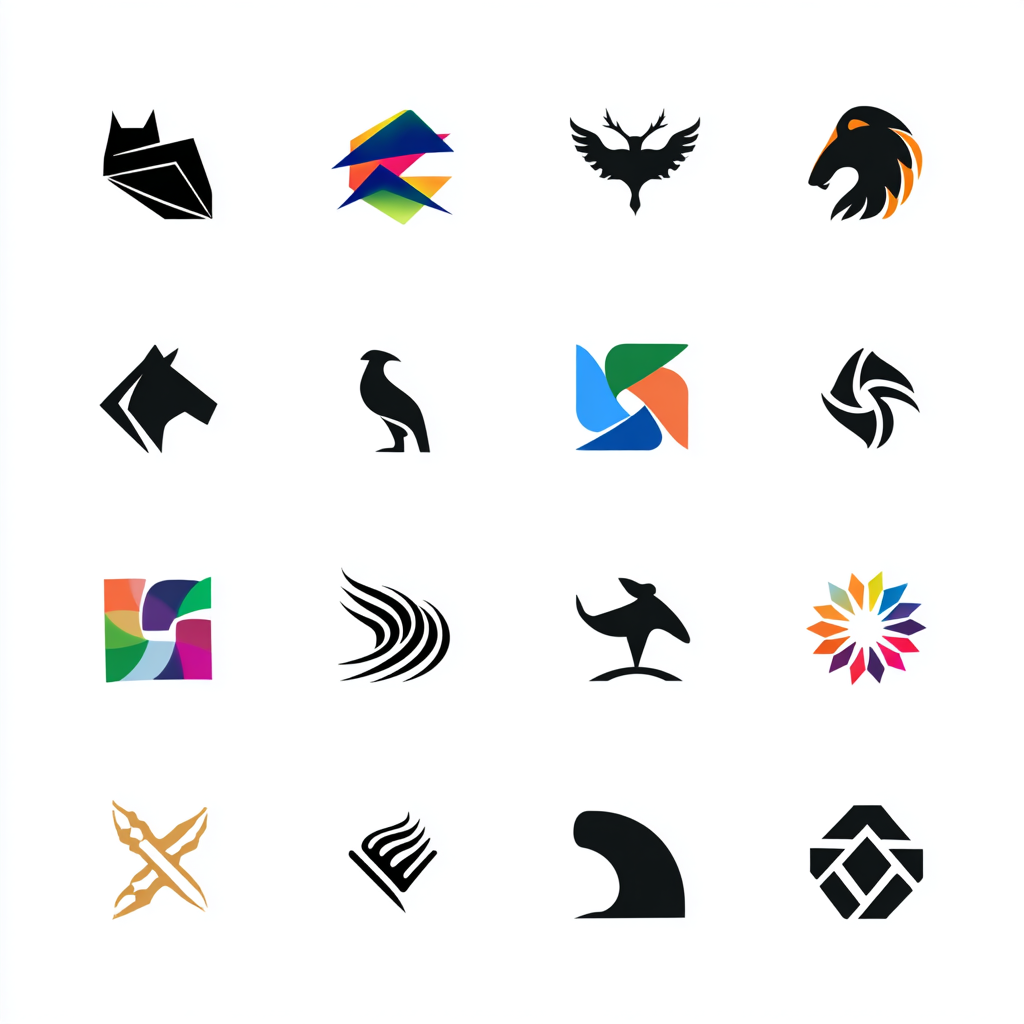
로고는 브랜드의 첫인상을 결정하는 아주 중요한 요소예요. 그런데 의외로 많은 사람들이 이걸 간과해서 안타까운 실패를 경험하곤 해요. 오늘은 실제 로고제작에서 벌어진 다양한 실패 사례들을 모아서 소개할게요. 이 글을 보면 '아, 이런 건 피해야겠구나!' 하고 고개를 끄덕이게 될지도 몰라요.
제가 생각했을 때 로고 하나에도 수많은 고민과 선택이 담겨야 해요. 브랜드 철학, 감성, 시선 끌기, 사용 용이성까지! 단순히 예쁘게만 만들었다고 좋은 로고가 아니에요. 그래서 오늘은 진짜 있었던 실패담들을 중심으로 이야기를 풀어볼게요. 공감도 되고, 배울 점도 가득하답니다!
그럼 이제 본격적으로 실패 사례를 하나씩 살펴볼게요. 절대 따라하면 안 되는 흔한 실수들! 🧨
❌ 너무 복잡한 디자인의 함정
로고는 단순함 속에 메시지를 담는 게 핵심이에요. 하지만 일부 사람들은 모든 걸 다 보여주고 싶어서 복잡하게 만들고 말아요. 꽃도 넣고, 건물도 넣고, 글자도 3개 이상… 결국 뭐가 핵심인지 모르게 되는 거죠.
예를 들어 A지역의 한 카페는 로고에 커피잔, 나무, 벤치, 고양이까지 넣었어요. 처음에는 "귀엽고 독특해요!"란 반응을 받았지만, 문제는 크기 조절이 안 되고 인쇄도 흐릿하게 나왔다는 점이었죠.
SNS 프로필 사진으로 넣으면 너무 작아서 알아보기 힘들고, 명함이나 포장지에 쓸 때마다 다르게 보였어요. 결국 6개월 만에 다시 제작하는 비용이 발생했어요.
디자인에 욕심내다 보면 되려 시선을 빼앗는 요소가 많아져 본질을 잃게 돼요. 로고는 눈에 띄고 기억되면 성공한 거예요. 복잡할수록 이 두 가지를 해치기 쉽죠!
🧩 복잡한 디자인의 문제점 요약표
문제 요소 결과 추천 해결 방법 디테일 과다 인쇄 품질 저하 단순화된 형태로 재디자인 색상 너무 많음 시각적 혼란 2~3가지 색상으로 구성 요소 간 간격 부족 읽기 어려움 여백 확보 복잡함보단 기억에 남는 단순함을 택하세요. 미니멀한 로고가 오히려 더 오랫동안 사랑받을 수 있어요! 😊
🎨 색상 선택의 실수
로고에서 색상은 감정을 전달하는 중요한 요소예요. 그런데 ‘예쁘니까’, ‘내가 좋아하니까’라는 기준으로 색상을 정하면 큰 실수를 할 수 있어요. 브랜드 메시지와 어울리지 않거나 가독성이 떨어지는 경우가 많거든요.
예를 들어, 어떤 IT 스타트업이 핑크색과 연두색을 조합해서 사용했는데, 이게 문제였어요. 귀여운 이미지로 보이긴 했지만, 신뢰감이 떨어진다는 피드백을 많이 받았어요. 결국 다시 파란색 계열로 리브랜딩했답니다.
색상은 무조건 브랜드의 속성과 연결돼야 해요. 빨간색은 열정, 파란색은 신뢰, 검은색은 고급스러움처럼요. 색만 잘 골라도 브랜드 이미지는 훨씬 강해질 수 있어요.
또 하나! 색상은 ‘보는 매체’에 따라 다르게 보일 수 있어요. 모니터, 모바일, 인쇄물에 따라 차이가 크기 때문에 꼭 다양한 환경에서 테스트해봐야 해요.
🌈 잘못된 색상 선택 예시표
선택 색상 문제 발생 상황 추천 해결책 형광 핑크 + 연두 눈에 피로, 신뢰도 저하 보색보다 유사색 활용 노랑 + 흰색 가독성 낮음 배경 대비 컬러 선택 회색 + 검정 분위기 너무 어두움 밝은 색 포인트 추가 색상 하나에도 전략이 필요해요. 감성과 기능, 전달력까지 고려해서 고르는 게 정말 중요해요. 무작정 예쁘기만 한 색은 오히려 독이 될 수 있답니다!
🔠 폰트 선택 실패 사례
폰트는 단순한 글씨체가 아니라 브랜드의 톤을 결정해요. 그런데 종종 너무 화려하거나 장난스러운 폰트를 써서 로고의 신뢰도를 낮추는 경우가 있어요. 읽기 어려운 폰트는 기능적으로도 큰 문제고요.
예를 들어 어떤 결혼정보회사가 손글씨 스타일의 귀여운 폰트를 사용했어요. 친근해 보일 순 있었지만, 신뢰와 품격을 전달하진 못했어요. 결과적으로 고객층과 맞지 않다는 피드백이 나왔고, 얼마 지나지 않아 다시 디자인을 바꿨답니다.
또 어떤 로고는 너무 얇은 폰트를 사용해서 축소했을 때 전혀 안 보이는 문제도 있었어요. 로고는 모바일에서도 또렷하게 보여야 하거든요. 그래서 일정 굵기의 명확한 폰트를 사용하는 게 좋아요.
폰트 선택 시 가장 중요한 건 ‘브랜드와 맞는가’, ‘가독성이 좋은가’, ‘어디서든 잘 보이는가’예요. 이 세 가지를 기준으로 고르면 큰 실수는 피할 수 있어요!
✍ 잘못된 폰트 선택 예시표
폰트 유형 실패 이유 대안 손글씨체 신뢰도 부족 고급 세리프체 사용 얇은 고딕체 작은 사이즈에서 안 보임 굵은 산세리프체 사용 장식 많은 폰트 가독성 저하 심플하고 균형 잡힌 폰트 로고 폰트는 ‘읽히는 게 먼저’예요. 감각적이면서도 쉽게 눈에 들어오는 디자인이 브랜드 이미지도 높여준답니다!
📏 일관성 없는 브랜딩 문제
로고는 단독으로도 중요하지만, 브랜드 전체 톤과 일관되어야 해요. 그런데 많은 사람들이 이걸 간과하고 로고만 예쁘게 만든 후 나머지 디자인 요소들과 따로 노는 현상이 종종 발생해요.
예를 들어 어떤 뷰티 브랜드는 로고는 블랙&화이트로 시크하게 만들었는데, 웹사이트와 포장은 핑크와 민트톤으로 귀엽게 꾸몄어요. 결과적으로 고객들은 “정체성이 뭐지?”라는 혼란을 느꼈답니다.
브랜딩은 통일성이 생명이에요. 로고, 컬러, 폰트, 이미지 스타일, 마케팅 문구까지 한 흐름으로 이어져야 해요. 그래야 브랜드가 탄탄하게 자리잡을 수 있어요.
브랜드 가이드를 만들면 이 문제를 방지할 수 있어요. 일관된 톤앤매너를 유지하면 고객들에게 신뢰를 줄 수 있고, 로고 하나만 봐도 “아, 그 브랜드구나!” 하고 떠오르게 만들 수 있어요.
📐 브랜딩 일관성 실패 유형
문제 요소 문제 상황 해결 전략 로고 스타일 불일치 웹/앱 디자인과 안 맞음 브랜드 가이드라인 작성 색상 사용 불균형 채널마다 색상 다름 메인컬러 1~2개 고정 폰트 혼용 인쇄물마다 느낌 다름 공통 폰트 지정 브랜드가 보여주는 모든 요소는 하나의 이야기처럼 이어져야 해요. 로고가 아무리 잘 만들어도 브랜딩 전체 흐름을 따르지 않으면 무용지물이 될 수 있어요!
🚫 타 브랜드 따라하다 망한 케이스
로고를 만들 때 "저 브랜드처럼 해줘요"라는 요청이 종종 들어와요. 하지만 이건 굉장히 위험한 접근이에요. 유사성 문제도 있지만, 그 브랜드만의 정체성을 흉내 낸다고 내 것이 되는 게 아니거든요.
한 의류 브랜드는 해외 명품 브랜드의 로고를 오마주한다고 했지만, 결과는 거의 표절에 가까운 유사 디자인이었어요. SNS에서는 "짝퉁 느낌 난다"는 평이 줄을 이었고, 오히려 브랜드 이미지를 망치고 말았어요.
로고는 ‘자기다움’을 드러내는 수단이에요. 남의 걸 베끼면 오히려 정체성이 없다는 인식을 심어주고, 법적인 문제도 생길 수 있어요. 창의적인 방향으로 자신의 이야기를 녹여내야 해요.
비슷한 디자인은 검색만 해도 수천 개가 나오는 시대예요. 이럴수록 고유성은 더 중요한 가치를 가지게 돼요. 따라하지 말고, 나만의 스토리로 로고를 만들어보세요!
🕵 표절로 의심받는 디자인 특징
디자인 요소 문제 대응 방안 비슷한 아이콘 사용 브랜드 구분 어려움 독자적 심볼 제작 글자 배열 모방 브랜드 혼동 구조 변경 색상 조합 동일 차별성 없음 브랜드 스토리 기반 색상 사용 진짜 멋진 로고는 누구의 것을 따라 한 게 아니라, 오롯이 나의 가치와 이야기를 담고 있어요. 그 진정성이 브랜드를 특별하게 만들어준답니다. 🔥
👂 피드백 무시한 결과
로고 디자인은 혼자 결정하기보단 여러 사람의 의견을 들어보는 게 좋아요. 하지만 간혹 자신의 취향만을 고집하다가 실패하는 경우가 있어요. "내가 좋으면 됐지!"라고 생각하지만, 결국 소비자는 내가 아니라 고객이니까요.
어떤 스타트업 대표는 지인들의 피드백을 무시하고 자신의 최애 색상과 문양으로 로고를 제작했어요. 결과는? 고객 반응은 차가웠고, 온라인 커뮤니티에서도 “너무 촌스럽다”, “브랜드와 안 맞는다”는 지적이 이어졌어요.
이런 상황을 방지하려면 시안을 만든 뒤 내부 직원, 기존 고객, 지인 등 다양한 의견을 수렴하는 과정이 꼭 필요해요. 객관적 시선은 브랜드 외형을 더 단단하게 만들어줘요.
피드백을 받는다고 모든 걸 바꿔야 하는 건 아니지만, 반복해서 나오는 의견은 반드시 귀 기울여야 해요. 실패한 로고의 공통점은 ‘고립된 결정’에서 비롯되곤 해요.
🗣 피드백 무시로 인한 손해 사례
무시된 피드백 결과 예방책 색 조합 촌스럽다 고객 이탈 테스트 그룹 운영 폰트 읽기 힘들다 가독성 문제 시안 테스트 너무 평범하다 브랜드 매력 없음 디자이너와 재논의 로고 디자인은 협업이에요. 브랜드를 대표하는 얼굴인 만큼, 다양한 시선을 반영하는 게 성공적인 결과로 이어진답니다. 😊
FAQ
Q1. 로고 디자인에 가장 흔한 실수는 뭐예요?
A1. 복잡한 디자인과 타 브랜드 유사 디자인이 가장 흔해요. 기억에 남기 어렵고 브랜드 고유성이 사라지기 쉬워요.
Q2. 로고에 몇 가지 색을 사용하는 게 좋을까요?
A2. 보통 2~3가지 색상을 추천해요. 메인 컬러 1개, 서브 컬러 1~2개가 이상적이에요.
Q3. 무료 폰트 사용해도 되나요?
Q5. 로고 하나로 브랜드 이미지가 완성되나요?
A5. 아니에요. 로고는 시작일 뿐이고, 전체 브랜딩 전략과 함께 움직여야 효과가 커져요.
Q6. 로고는 얼마나 자주 바꿔도 되나요?
A6. 가능하면 자주 바꾸지 않는 게 좋아요. 브랜드 인식에 혼란을 줄 수 있거든요.
Q8. 모바일에서 잘 보이는 로고는 어떻게 만들어야 하나요?
A8. 작은 크기에서도 식별 가능하도록 단순하고 선명한 형태로 디자인하는 게 핵심이에요.